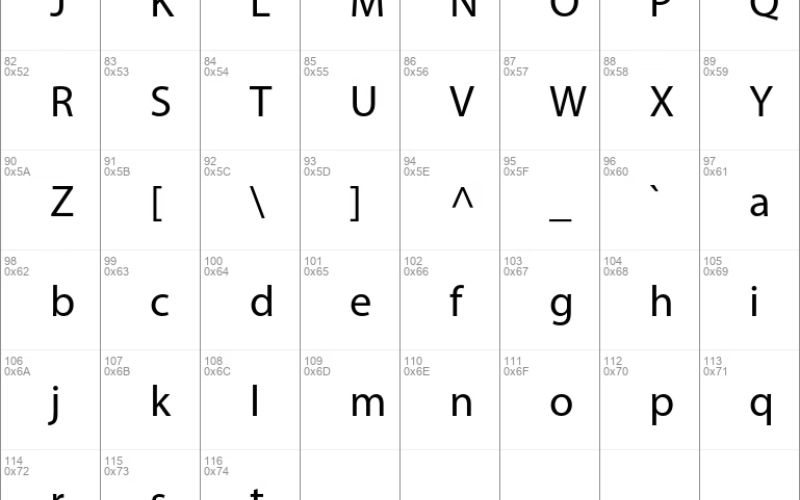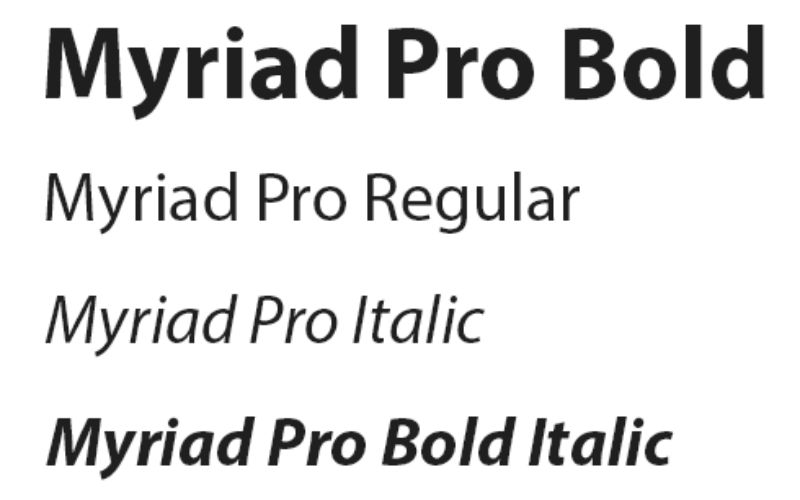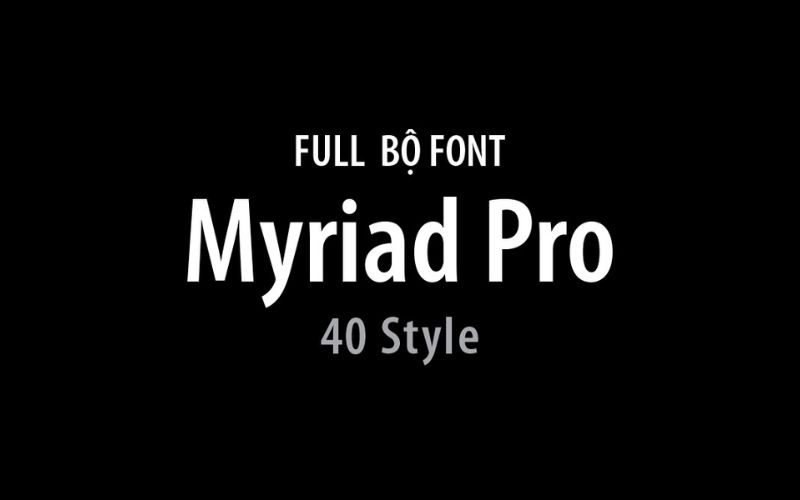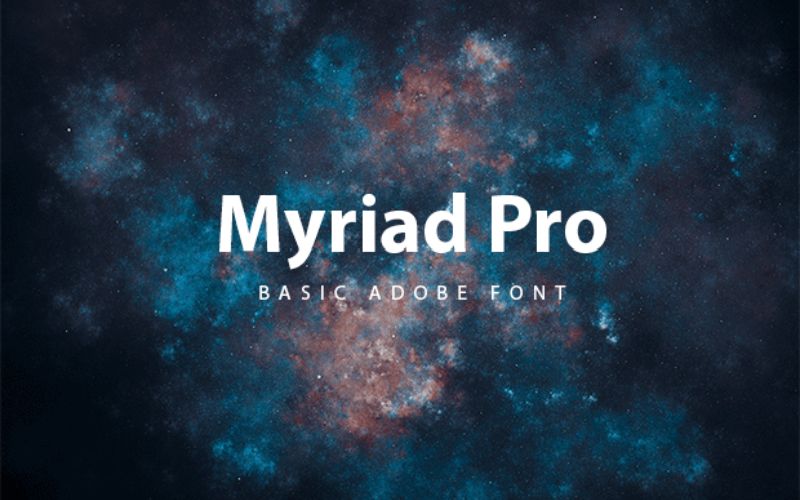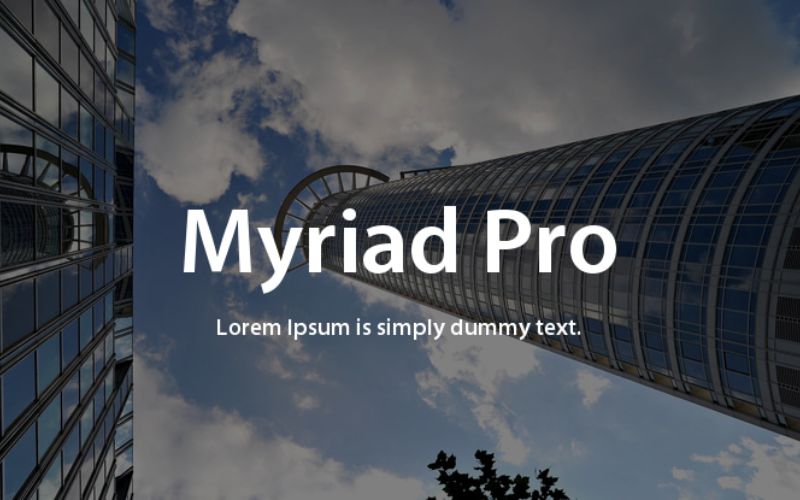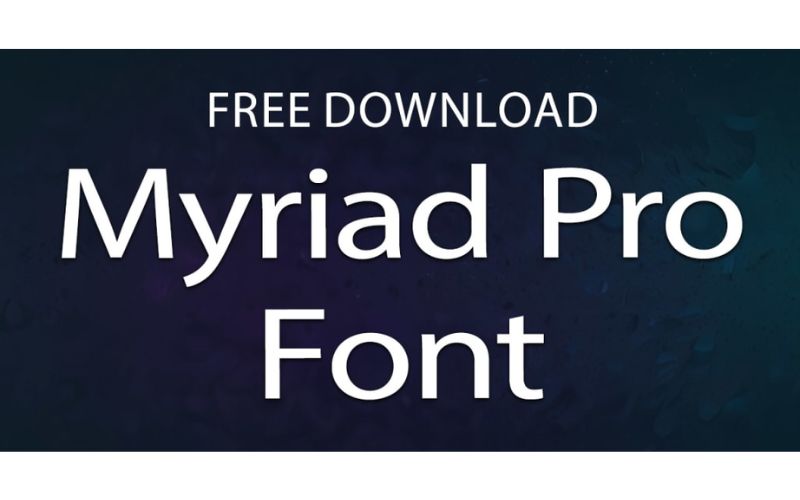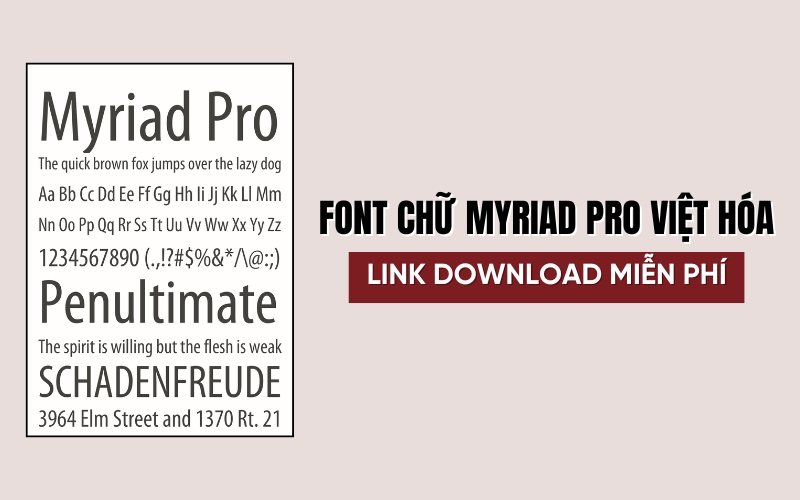
Nếu bạn là designer, dân in ấn hay làm việc với đồ họa chuyên nghiệp, chắc hẳn đã từng nghe qua cái tên font chữ Myriad Pro Việt hóa – một trong những kiểu chữ được sử dụng rộng rãi nhất hiện nay. Với thiết kế hiện đại, cân đối và dễ đọc, Myriad Pro không chỉ phù hợp cho các dự án thương hiệu, thiết kế logo mà còn được ưa chuộng trong in ấn, trình bày văn bản và quảng cáo. Trong bài viết này, hãy cùng Vietkey khám phá những đặc điểm nổi bật của font Myriad Pro, lợi ích khi dùng phiên bản Việt hóa và cách tải, cài đặt nhanh chóng để tối ưu trải nghiệm thiết kế của bạn.
Font chữ Myriad Pro Việt hóa là gì?
Font chữ Myriad Pro Việt hóa là phiên bản được chỉnh sửa và bổ sung ký tự tiếng Việt của font gốc Myriad Pro, một kiểu chữ sans-serif nổi tiếng do Adobe phát triển. Font này sở hữu đường nét mềm mại, cân đối và hiện đại, giúp văn bản trở nên rõ ràng và chuyên nghiệp hơn. Phiên bản Việt hóa giữ nguyên tinh thần thiết kế nguyên bản nhưng được bổ sung đầy đủ dấu tiếng Việt như ă, â, ê, ô, ơ, ư, đ…, đảm bảo hiển thị chính xác trên mọi nền tảng.
Nhờ sự hài hòa giữa tính thẩm mỹ và khả năng ứng dụng cao, Myriad Pro Việt hóa được sử dụng phổ biến trong thiết kế logo, ấn phẩm quảng cáo, website, banner hay tài liệu trình chiếu. Đây là lựa chọn lý tưởng cho những ai muốn kết hợp giữa sự sang trọng, hiện đại và dễ đọc trong các sản phẩm thiết kế của mình.
Đặc điểm nổi bật của font Myriad Pro Việt hóa
Font chữ Myriad Pro Việt hóa được ưa chuộng không chỉ vì tính thẩm mỹ mà còn bởi khả năng ứng dụng linh hoạt trong nhiều lĩnh vực thiết kế. Dưới đây là những đặc điểm nổi bật giúp font này trở thành lựa chọn hàng đầu của các nhà thiết kế và marketer hiện nay:
- Thiết kế hiện đại, tinh tế: Myriad Pro mang phong cách sans-serif với đường nét tròn đều, khoảng cách chữ hợp lý, giúp văn bản dễ đọc và mang cảm giác chuyên nghiệp.
- Hỗ trợ tiếng Việt đầy đủ: Phiên bản Việt hóa được bổ sung đầy đủ dấu và ký tự tiếng Việt, đảm bảo hiển thị chính xác trên mọi phần mềm và nền tảng.
- Đa dạng trọng lượng (weight): Font có nhiều phiên bản như Light, Regular, SemiBold, Bold, giúp người dùng dễ dàng phối hợp trong thiết kế tiêu đề và nội dung.
- Ứng dụng linh hoạt: Phù hợp cho thiết kế logo, banner, catalogue, poster, ấn phẩm quảng cáo và website nhờ khả năng thể hiện rõ nét và sang trọng.
- Myriad Pro Black Semi Condensed Việt hóa
- Myriad Pro Black Semi Condensed Italic Việt hóa
- Myriad Pro Light Việt hóa
- Myriad Pro Light Italic Việt hóa
- Myriad Pro Regular Việt hóa
- Myriad Pro Regular Italic Việt hóa
- Myriad Pro Semibold Việt hóa
- Myriad Pro Semibold Italic Việt hóa
- Myriad Pro Bold Việt hóa
- Myriad Pro Bold Italic Việt hóa
- Myriad Pro Black Việt hóa
- Myriad Pro Black Italic Việt hóa
- Myriad Pro Light SemiExtended Việt hóa
- Myriad Pro Light SemiExtended Italic Việt hóa
- Myriad Pro SemiExtended Việt hóa
- Myriad Pro SemiExtended Italic Việt hóa
- Myriad Pro Semibold SemiExtended Việt hóa
- Myriad Pro Semibold SemiExtended Italic Việt hóa
- Myriad Pro Bold SemiExtended Việt hóa
- Myriad Pro Bold SemiExtended Italic Việt hóa
- Myriad Pro Black SemiExtended Việt hóa
- Myriad Pro Black SemiExtended Italic Việt hóa
Ứng dụng của font Myriad Pro Việt hóa trong thiết kế
Nhờ kiểu dáng hiện đại, dễ đọc và khả năng hiển thị ổn định, font Myriad Pro Việt hóa được ứng dụng rộng rãi trong nhiều lĩnh vực thiết kế khác nhau. Đây là một trong những font chữ linh hoạt, có thể sử dụng cho cả dự án sáng tạo lẫn chuyên nghiệp.
- Thiết kế thương hiệu và logo: Myriad Pro mang lại cảm giác sang trọng, tinh gọn, giúp logo dễ nhận diện và phù hợp với nhiều phong cách thương hiệu từ công nghệ, giáo dục đến thời trang.
Font chữ Myriad Pro Việt hóa không chỉ mang đến vẻ đẹp hiện đại, chuyên nghiệp mà còn đảm bảo khả năng hiển thị tiếng Việt hoàn hảo trên mọi nền tảng. Nhờ thiết kế cân đối, dễ đọc và ứng dụng linh hoạt, Myriad Pro trở thành lựa chọn lý tưởng cho các nhà thiết kế, marketer hay doanh nghiệp muốn xây dựng hình ảnh thương hiệu chỉn chu.